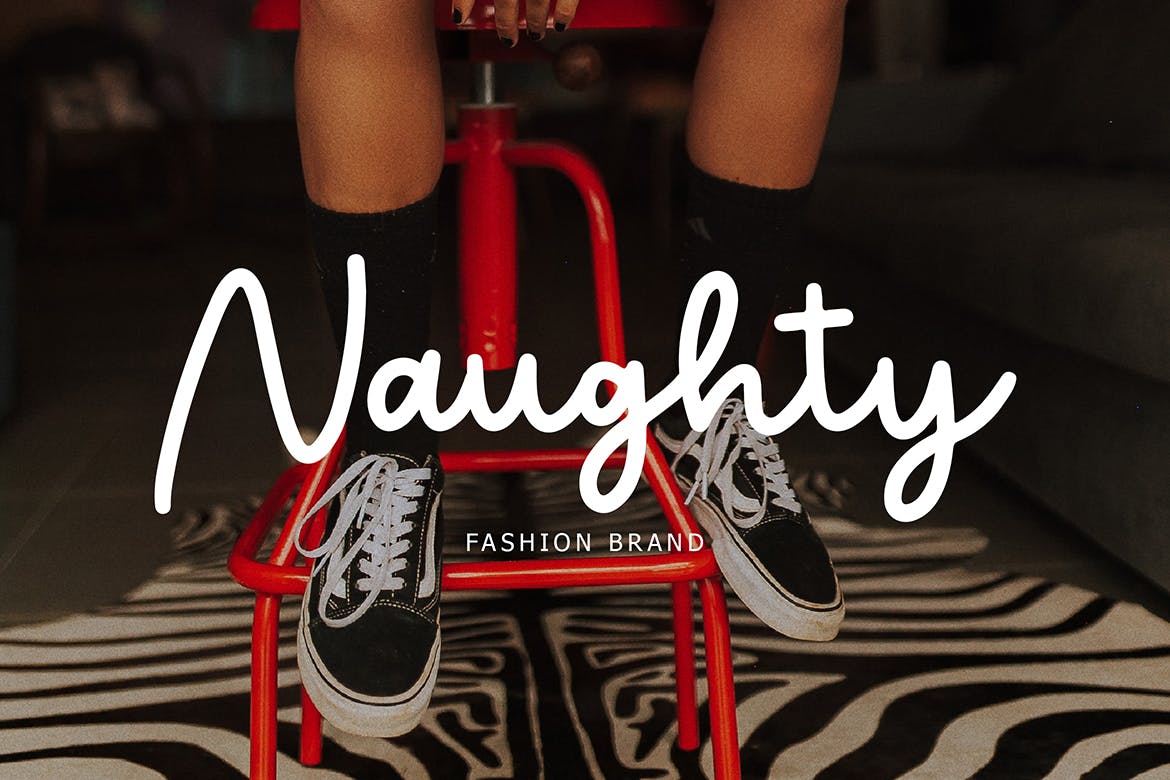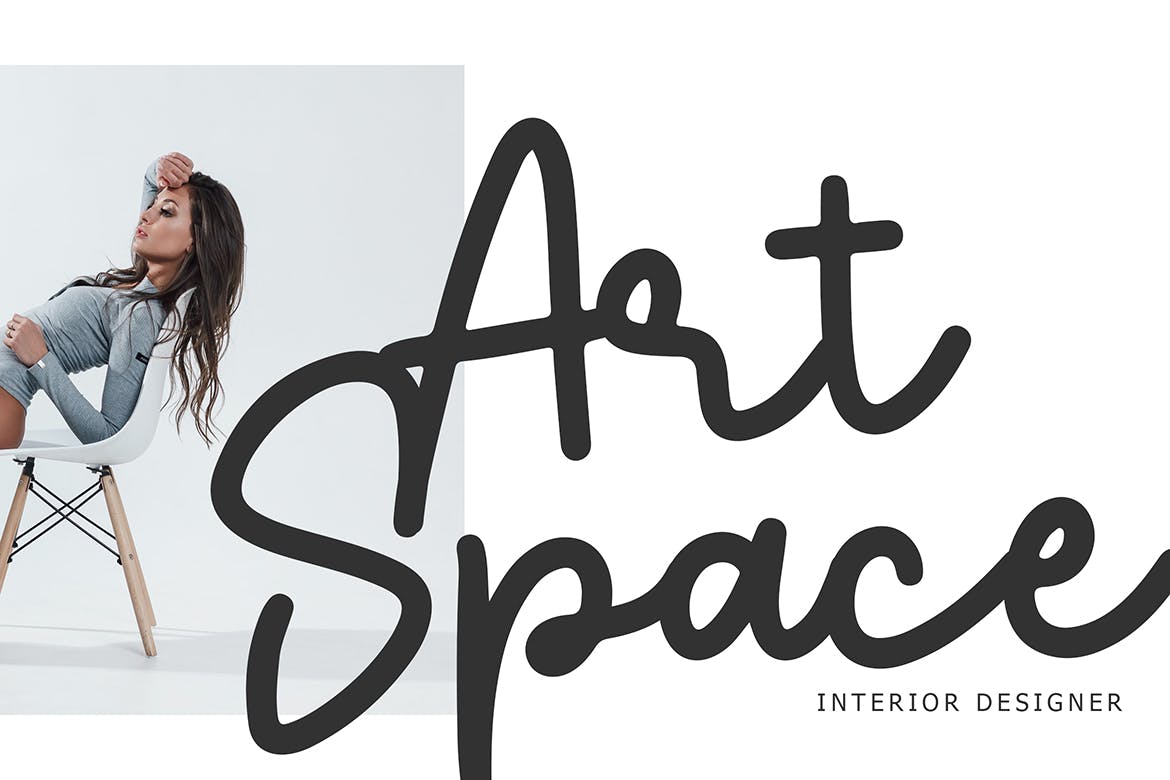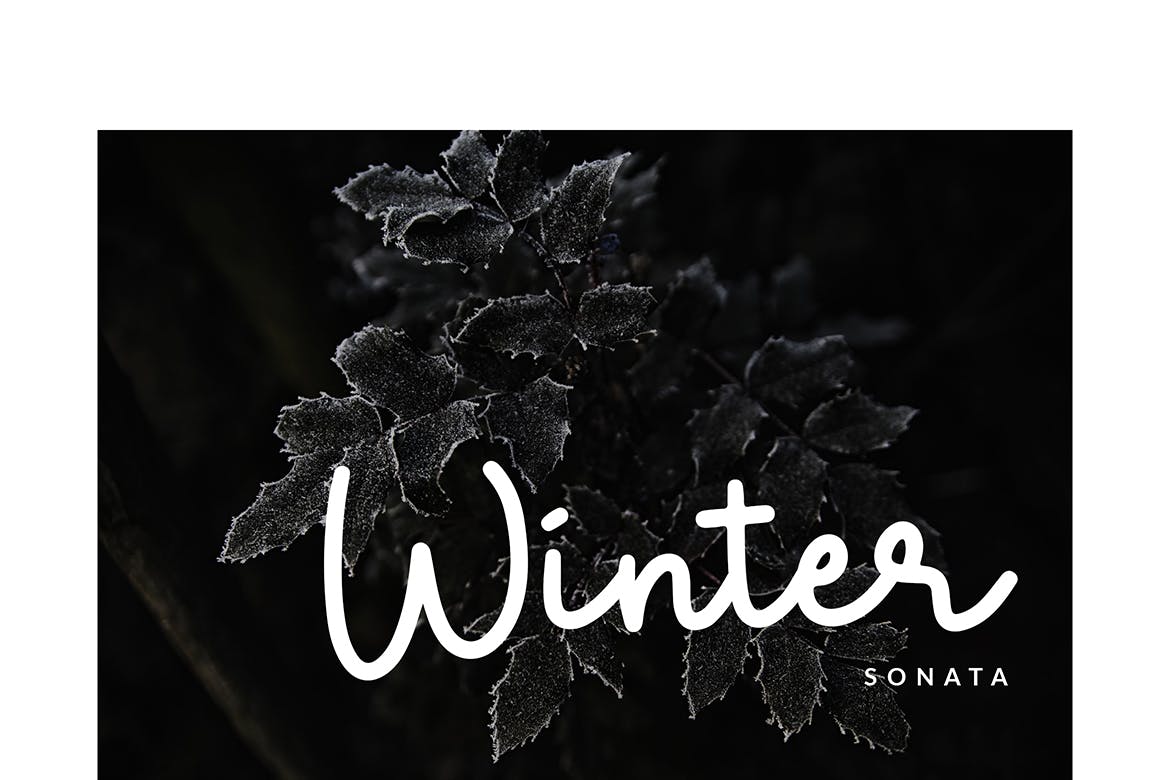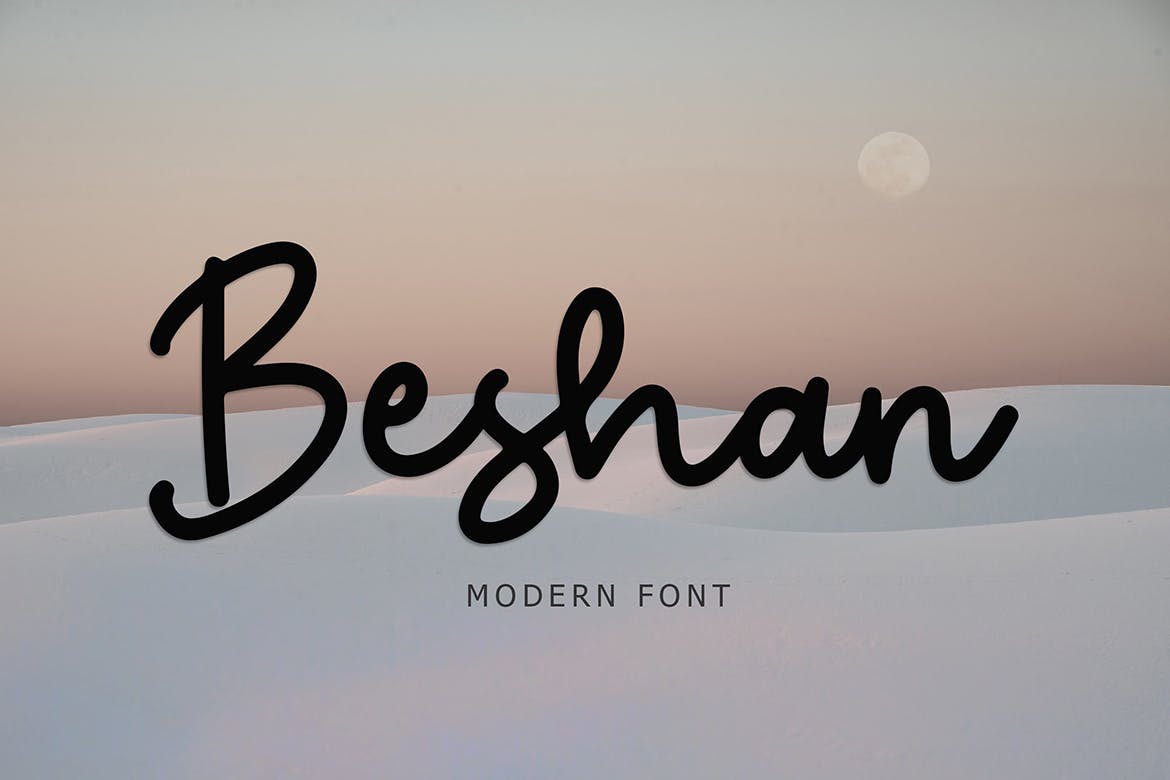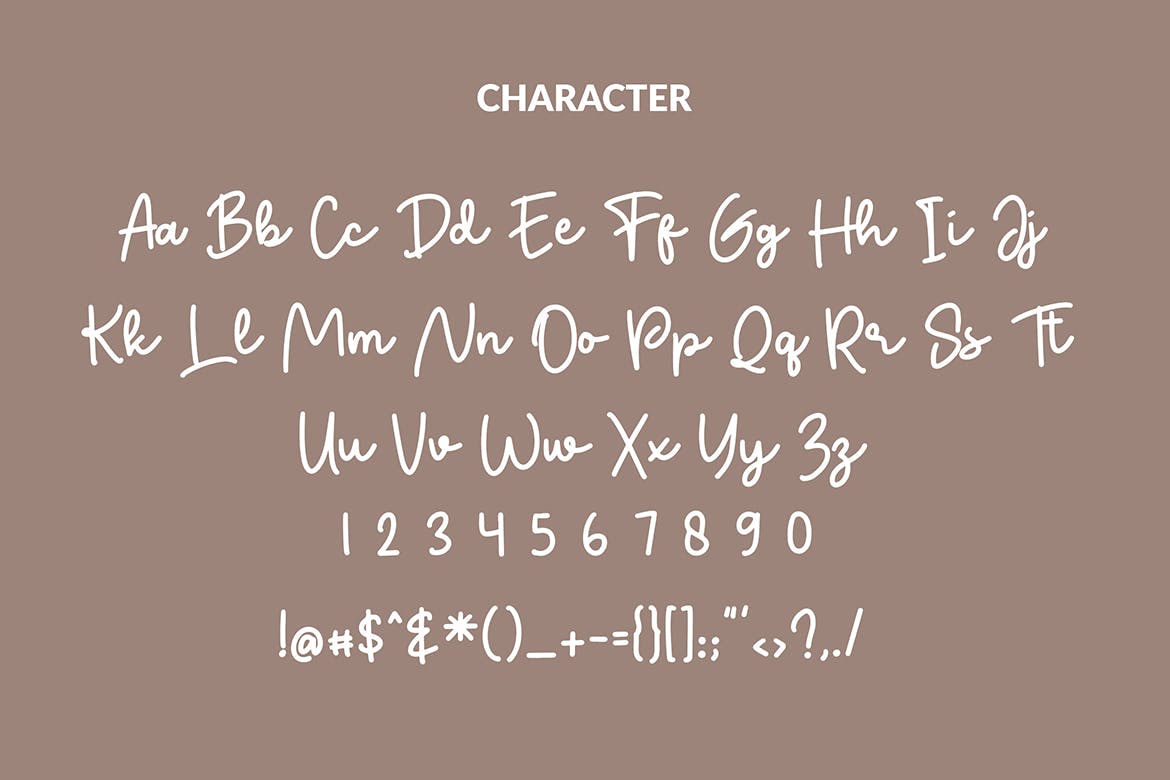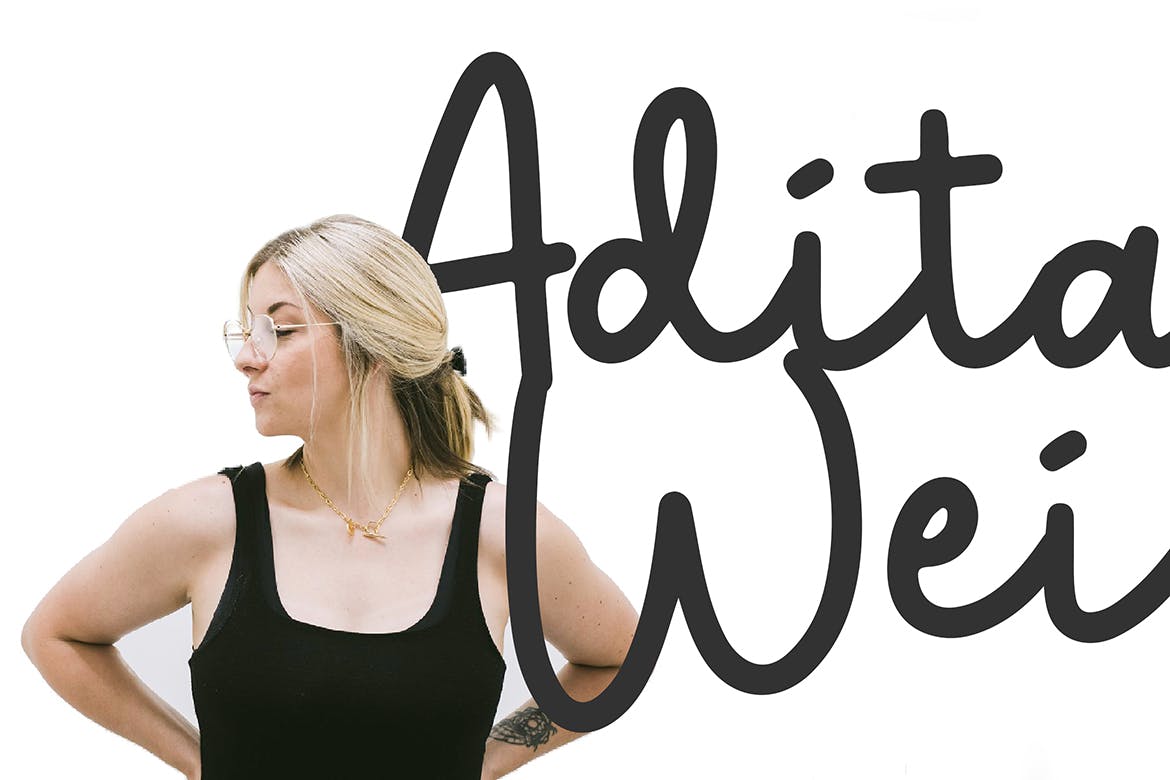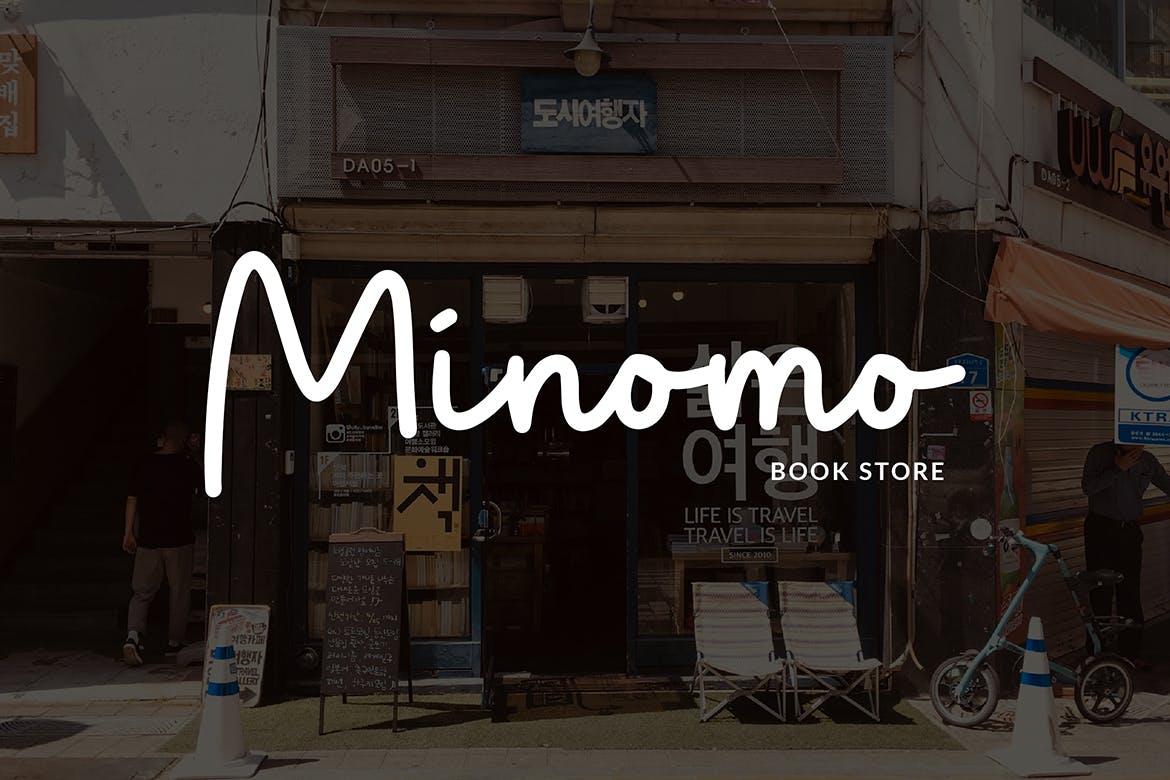
فونت بشن یک فونت مدرن و زیبا با طراحی خطی است که میتواند متن شما را شیک، لوکس و امروزی جلوه دهد!
فونت بشن برای پروژههای برندینگ، طراحی لوگو، طراحیهای عروسی، پستهای شبکههای اجتماعی، تبلیغات، بستهبندی محصولات، طراحی تیشرت، طراحی محصولات، برچسبها، عکاسی، واترمارک، دعوتنامه، لوازمالتحریر و هر پروژهای مناسب است.